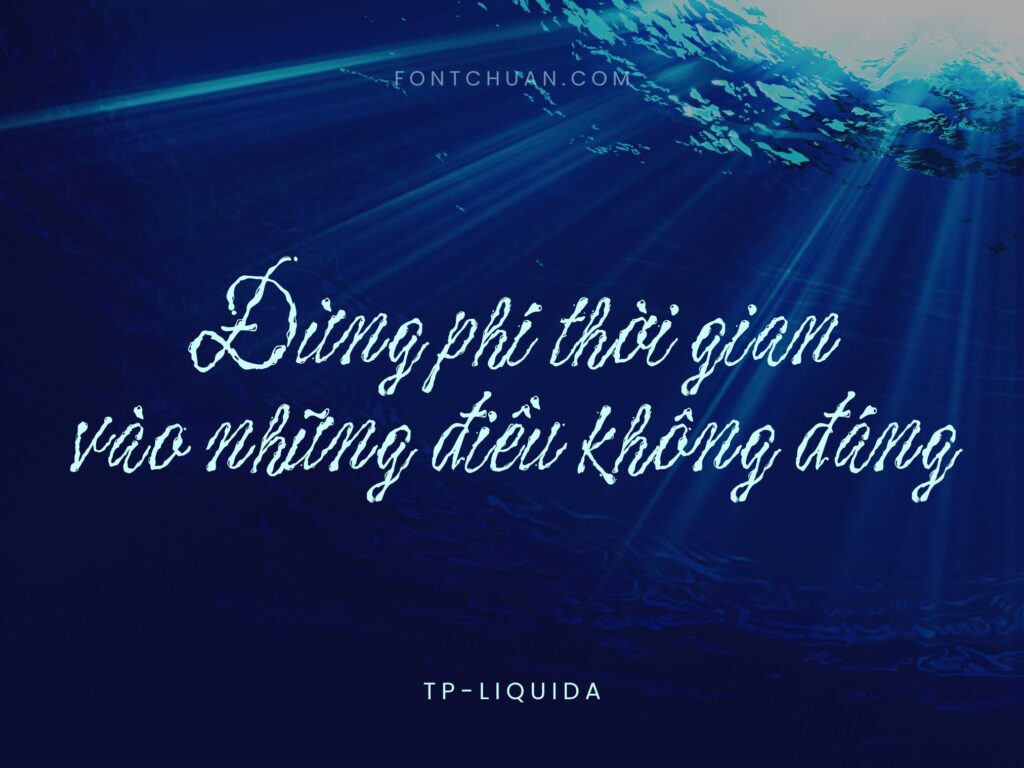
Font TP Liquida Việt Hóa
Liquida là một font chữ viết tay độc đáo, được thiết kế bởi Resistenza Type Foundry. Font này nổi bật với độ nghiêng và các ký tự lấy cảm hứng từ giọt nước, tạo hiệu ứng chảy độc đáo. Được vẽ hoàn toàn bằng cọ và mực óc chó, Liquida mang lại cảm giác tự nhiên, mềm mại và linh hoạt trong thiết kế. Với phong cách tinh tế, Liquida cũng có thể được sử dụng như một Font cổ trang, đem lại vẻ hoài cổ và nghệ thuật cho các dự án mang tính lịch sử hoặc cổ điển. Font đã được Việt hóa để hỗ trợ tiếng Việt bởi Tuỳn Pucca, mở rộng phạm vi sử dụng cho người dùng Việt Nam. Font này được sưu tầm và chia sẻ bởi thành viên của Font Chuẩn, đáp ứng nhu cầu sử dụng trong các dự án thiết kế đa dạng.
Đặc điểm thiết kế của Liquida bao gồm các nét chữ nghiêng và hiệu ứng chảy độc đáo, tạo cảm giác mềm mại và linh hoạt. Font này phù hợp cho các ứng dụng như thiết kế tiêu đề, poster, bao bì sản phẩm và các dự án sáng tạo khác. Các ngành nghề phù hợp bao gồm quảng cáo, nghệ thuật và thiết kế đồ họa.